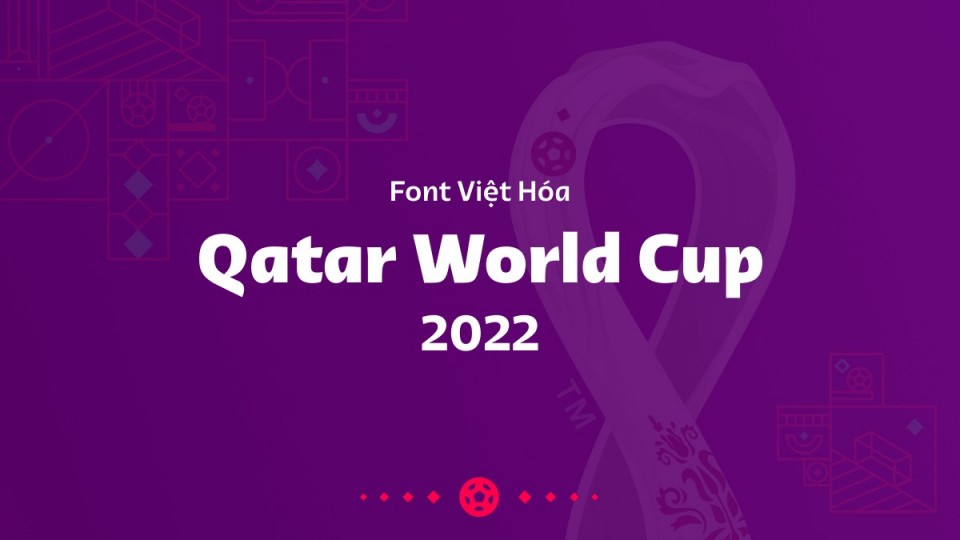
Giới thiệu về bộ Font Việt Hóa Qatar 2022
Chào mừng các bạn đến với kho lưu trữ tài liệu thiết kế chuyên nghiệp. Trong thế giới đồ họa, việc lựa chọn đúng Font Chữ đóng vai trò quyết định đến linh hồn của tác phẩm. Đặc biệt, bộ Font Việt Hóa Qatar 2022 đã trở thành cơn sốt kể từ kỳ World Cup lịch sử. Đây là bộ phông chữ lấy cảm hứng từ thư pháp Ả Rập, kết hợp nét hiện đại của nghệ thuật đương đại, tạo nên sự uyển chuyển nhưng vô cùng mạnh mẽ cho các biểu ngữ thể thao.
Đặc điểm nổi bật của Font Việt Hóa Qatar 2022
Bộ font này không chỉ dừng lại ở việc mô phỏng các ký tự Latinh theo phong cách Trung Đông mà còn được tinh chỉnh kỹ lưỡng để phù hợp với bảng mã tiếng Việt. Các dấu câu được sắp xếp cân đối, không làm mất đi cấu trúc đặc trưng của chữ gốc. Font Việt Hóa Qatar 2022 giúp các bạn học sinh và giáo viên dễ dàng tạo ra những bài trình chiếu, tờ rơi hoặc áo lớp mang đậm tinh thần bóng đá quốc tế.
Ứng dụng thực tế trong giáo dục và thiết kế
Với sự độc đáo trong từng nét vẽ, bộ font này cực kỳ phù hợp cho các tiêu đề lớn, banner sự kiện nhà trường hoặc các bảng tin học đường. Sự kết hợp giữa nét thanh và nét đậm giúp thông tin trở nên nổi bật, thu hút ánh nhìn ngay từ giây phút đầu tiên. Việc sử dụng bộ chữ này cũng là cách để chúng ta tìm hiểu thêm về văn hóa đồ họa của các quốc gia khác trên thế giới.